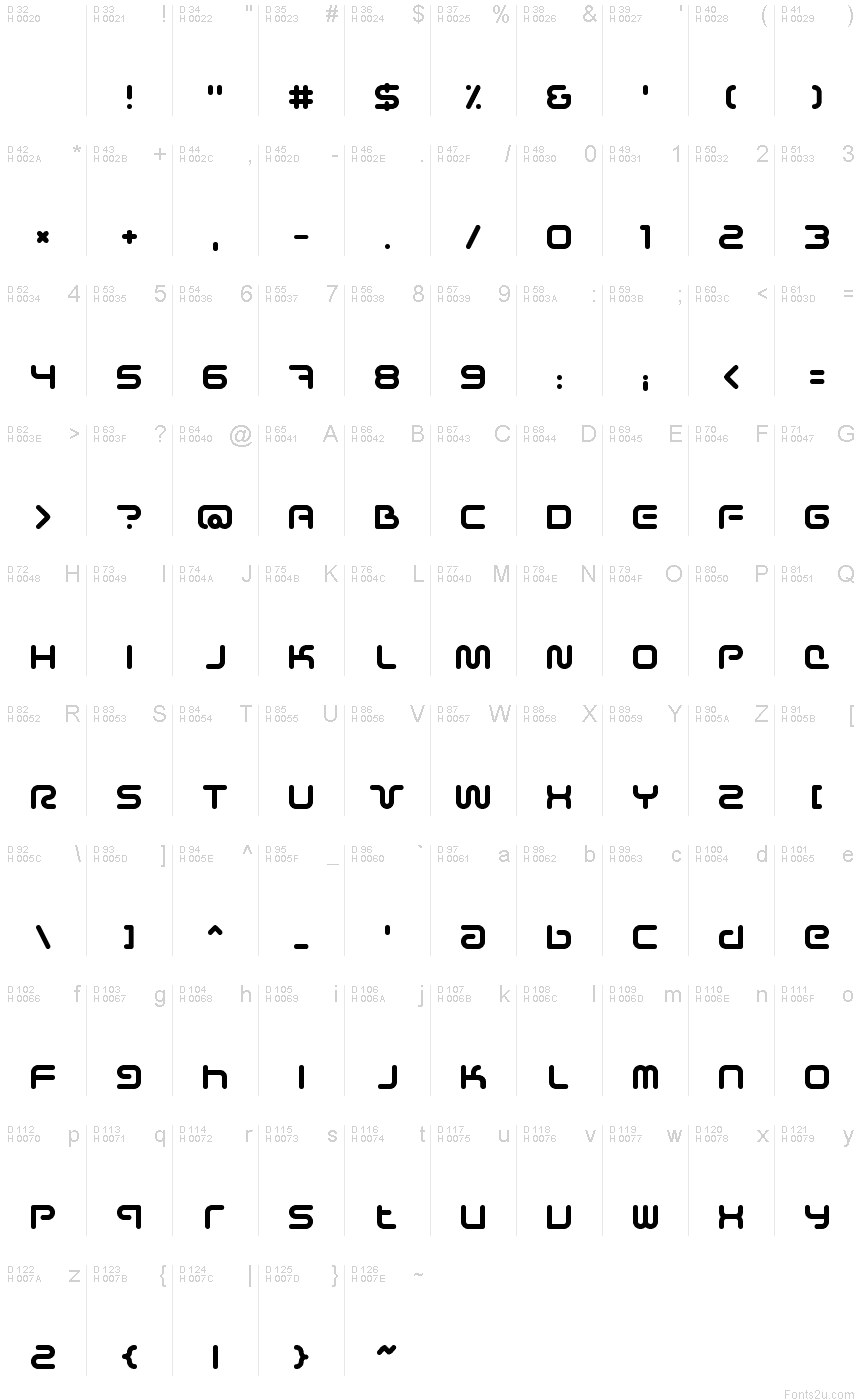
Sci Fied, creata da dustBUST Fonts, è un carattere display gratuito in maiuscolo dal gusto futuristico e con un tocco retro-sci-fi. Le lettere sono caratterizzate da tratti spessi e arrotondati con curve squadrate, impreziosite da tagli aperti e giunzioni nette che conferiscono al lettering uno stile da design spaziale d'altri tempi, evitando l'effetto freddo dell'industria pesante.
È perfetta per titoli di poster, loghi di videogame, flyer, copertine e ogni progetto in cui poche lettere debbano comunicare l'atmosfera all'istante. Ideale come font gratuito per branding, grafiche per soundtrack, eventi tech o iniziali, funziona perché le maiuscole appaiono profilate, compatte e leggermente cinematografiche, senza risultare mai troppo cariche.